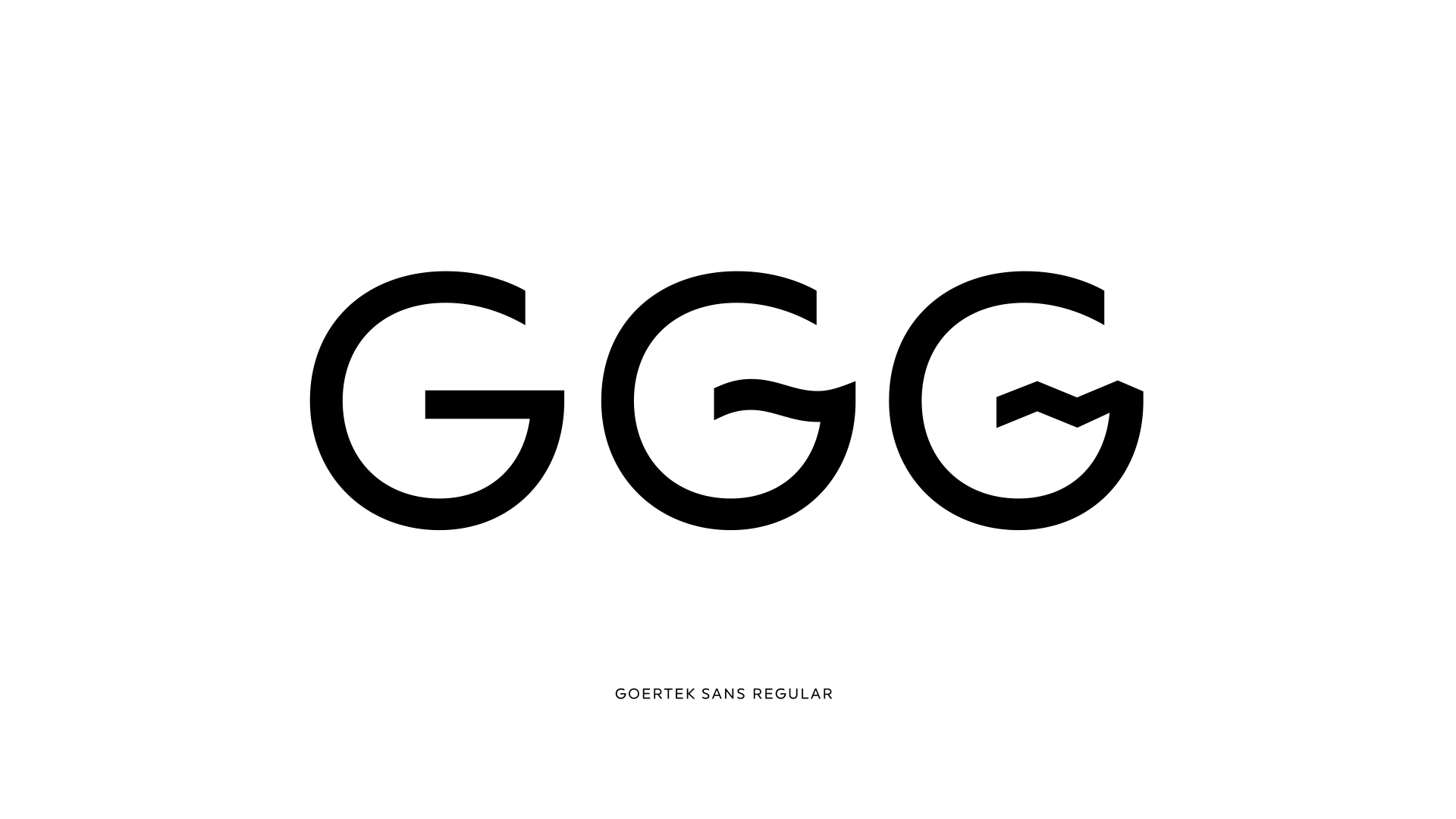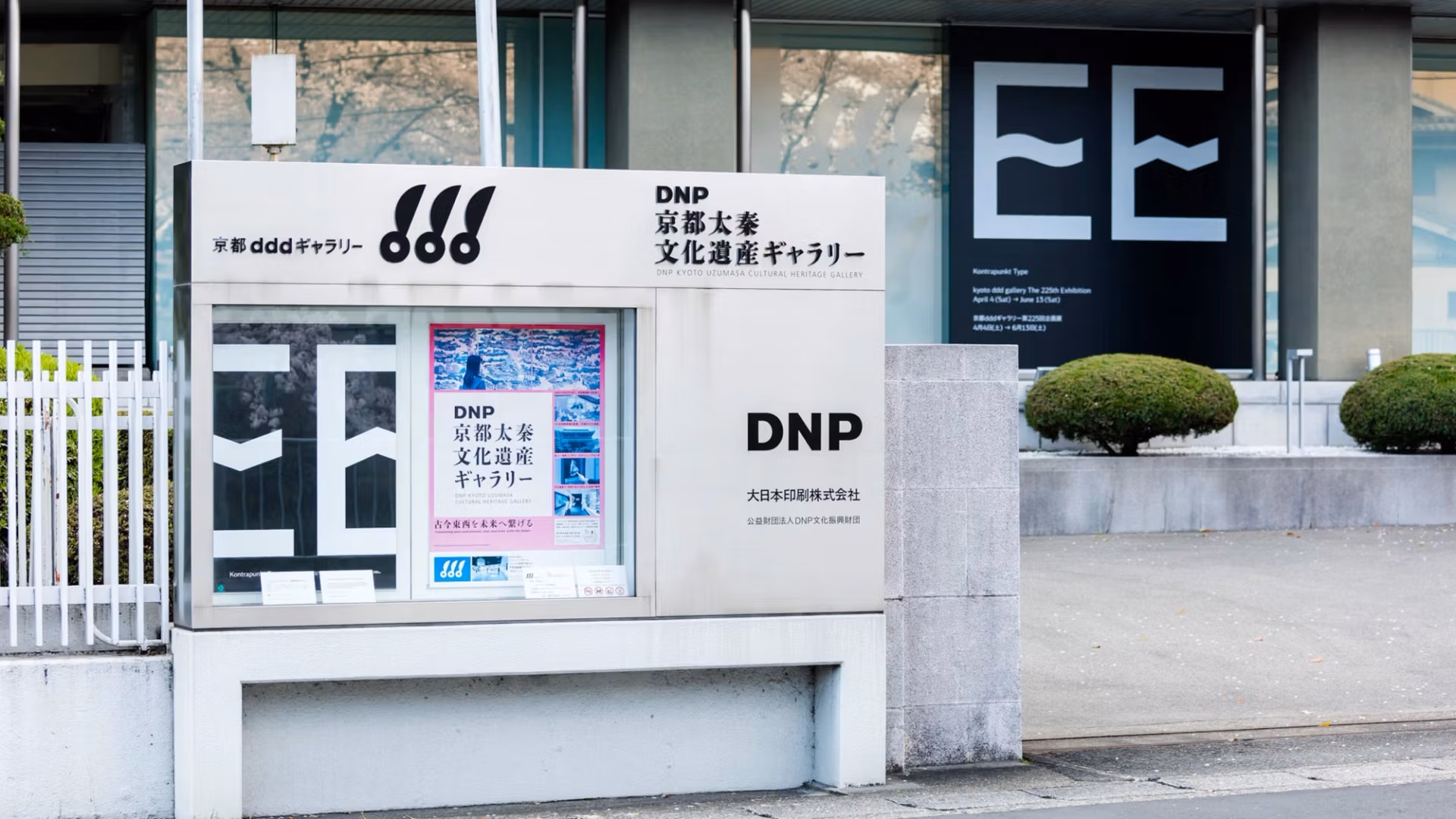
Kontrapunkt, 2017
Goertek Typeface es un sistema tipográfico sensible al sonido desarrollado para la compañía de audio Goertek. El tipo reacciona en tiempo real al entorno auditivo, alterando su forma específicamente según las variaciones en el volumen y la frecuencia del sonido ambiente.
Su principal aportación es la capacidad de vibrar para imitar el movimiento de las ondas sonoras, donde los sonidos más fuertes generan una mayor amplitud visual. Esto permite que el tipo actúe como una entidad dinámica que visualiza el sonido.
La relevancia de este proyecto para la investigación es que ejemplifica la aplicación de la tipografía interactiva en un contexto de branding corporativo. Demuestra cómo los datos externos pueden modular la morfología del glifo para construir una identidad visual viva y coherente con la actividad de la marca.
- Década: Década de 2010
- Función: Identidad visual
- Contexto: Branding
- Grado de interactividad: Interacción débil o reactiva
- Input multimodal: No
- Tipo de input: Sonido
- Tipo de output: Transformación morfológica
- Tecnología empleada: Desarrollo a medida
- Alfanumérica: Sí
- Mantiene codificación textual: No